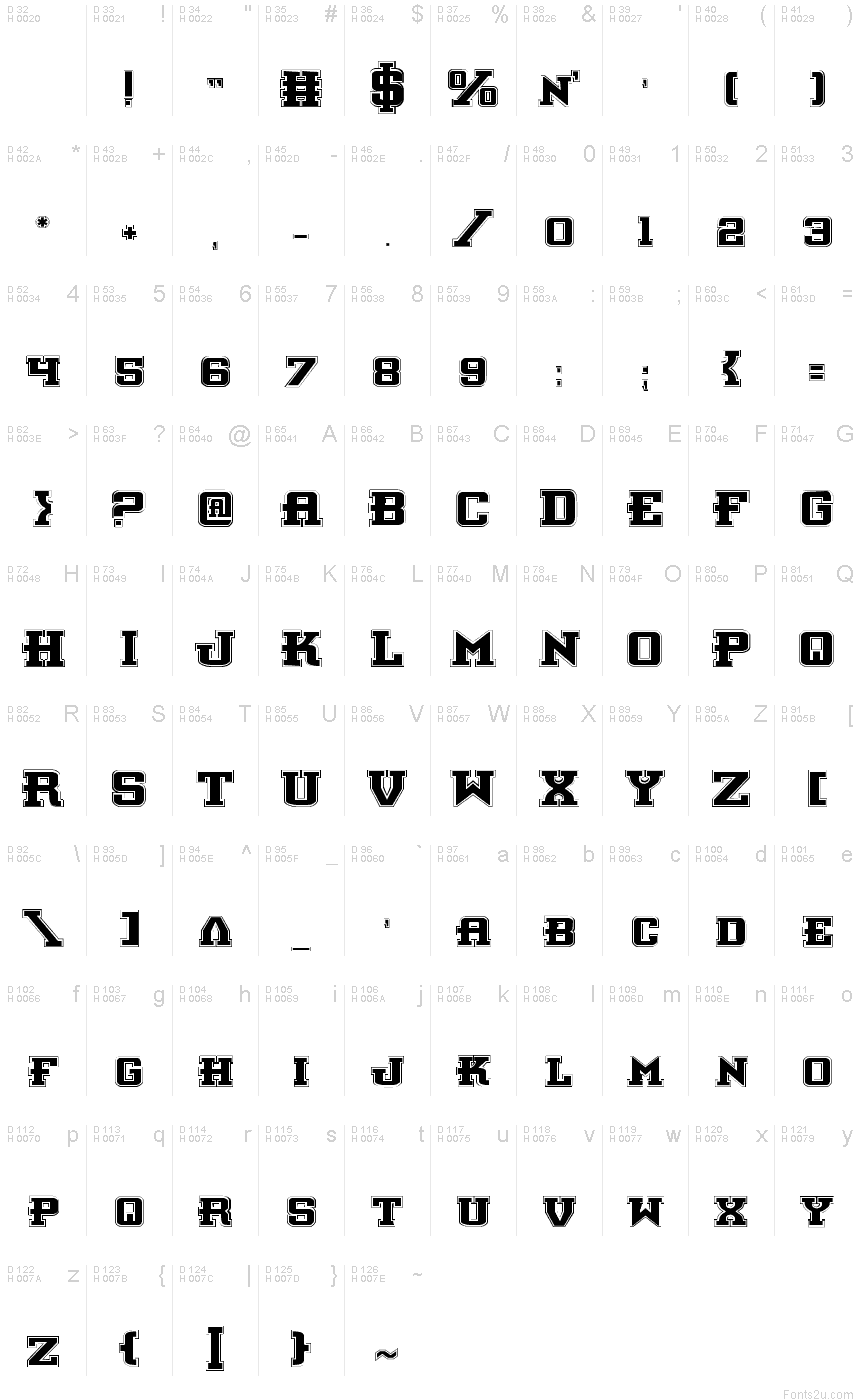
Interceptor Pro od Iconian Fonts to darmowy, sportowy krój displayowy w stylu varsity o nowoczesnym, wyrazistym charakterze. Litery są szerokie i kanciaste, zbudowane z ciężkich bloków otoczonych jasnym konturem, co nadaje krojowi warstwowy, odznakowy wygląd.
Świetnie sprawdzi się w logotypach drużyn, nagłówkach plakatów, okładkach, planszach tytułowych i monogramach, gdzie masywne, obrysowane litery pozwalają wyróżnić krótkie hasła. Jako darmowy font, Interceptor Pro idealnie nadaje się do brandingu e-sportowego, grafik na imprezy szkolne, gadżetów inspirowanych strojami sportowymi oraz nagłówków w stylu retro arcade, szczególnie gdy zależy Ci na tym, aby wielkie litery brzmiały głośno i stanowiły zwartą całość.
Interceptor Pro